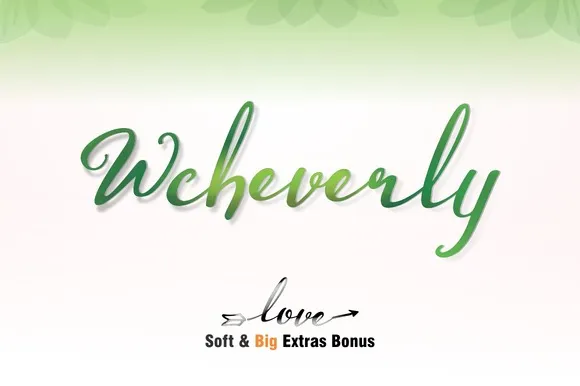
Wcheverly Script Font – Fonte Grátis
Wcheverly Script Font
A Wcheverly Script é uma nova adição à família de fontes script que oferece um toque moderno e sofisticado. Desenvolvida cuidadosamente, cada letra foi redescrita e refinada para atingir a perfeita simularidade com o estilo da escrita à mão. Esta fonte proporciona uma experiência única, onde a elegância e a modernidade se mesclam de forma harmoniosa. Se você está procurando por uma fonte que combine charme pessoal com um toque contemporâneo, Wcheverly Script é definitivamente para você. Escolha essa fonte para seus projetos, pois ela não apenas adicionará um toque diferenciado, mas também certamente deixará sua marca de forma elegante e sofisticada.